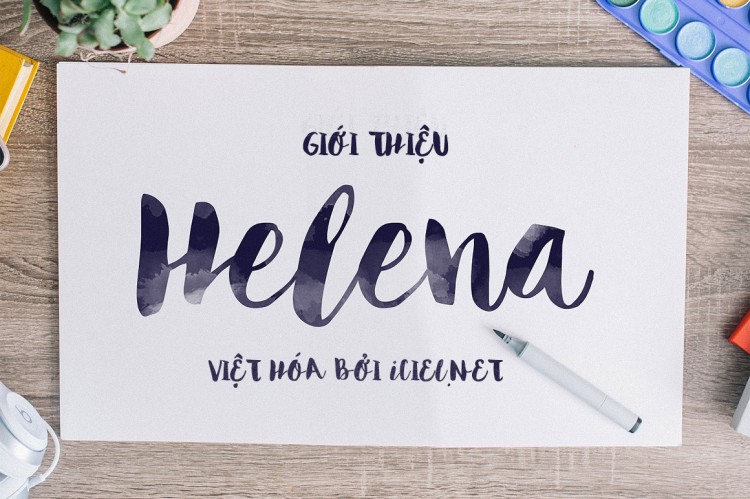
Giới thiệu về Font việt hoá iCiel Helena kiểu màu nước
Trong thế giới đồ họa hiện đại, việc lựa chọn Font Chữ phù hợp đóng vai trò quyết định đến linh hồn của tác phẩm. Font việt hoá iCiel Helena kiểu màu nước là một bộ phông chữ mang phong cách thủ công đầy tinh tế, mô phỏng những nét vẽ tay mềm mại bằng cọ. Điểm đặc biệt của bộ font này chính là sự kết hợp hoàn hảo giữa nét chữ thanh thoát và hiệu ứng loang màu nước tự nhiên, tạo cảm giác gần gũi nhưng không kém phần sang trọng. Đối với các bạn học sinh hay thầy cô giáo, đây là lựa chọn tuyệt vời để trang trí bìa báo tường, thiệp chúc mừng hoặc các bài thuyết trình nghệ thuật đầy cảm hứng.
Đặc điểm nổi bật của iCiel Helena
Bộ font này sở hữu những đường nét uốn lượn nhịp nhàng, tạo nên một tổng thể hài hòa và sống động. Khác với các phông chữ kỹ thuật số khô cứng, iCiel Helena mang lại cảm giác ấm áp của những sản phẩm thủ công. Việc được việt hoá chỉn chu giúp người dùng hoàn toàn yên tâm khi gõ tiếng Việt mà không lo lỗi hiển thị dấu câu hay các ký tự đặc biệt, đảm bảo tính thẩm mỹ cao nhất cho mọi thiết kế.
Ứng dụng Font việt hoá iCiel Helena kiểu màu nước trong giáo dục và đời sống
Sáng tạo trong học đường
Các em học sinh có thể sử dụng Font việt hoá iCiel Helena kiểu màu nước để thiết kế tiêu đề cho các dự án học tập, làm nhãn vở hay trang trí sổ tay cá nhân. Vẻ ngoài bay bổng của nó giúp khơi gợi khả năng sáng tạo và tình yêu nghệ thuật trong môi trường sư phạm.
Thiết kế thương hiệu và quà tặng
Bên cạnh ứng dụng học đường, font chữ này còn rất được ưa chuộng trong việc thiết kế logo cho các tiệm hoa, thiệp mời đám cưới hay các ấn phẩm quảng cáo mỹ phẩm. Sự mềm mại của nét màu nước tạo nên dấu ấn riêng biệt, thu hút ánh nhìn ngay từ lần đầu tiên.
Kết luận